底线
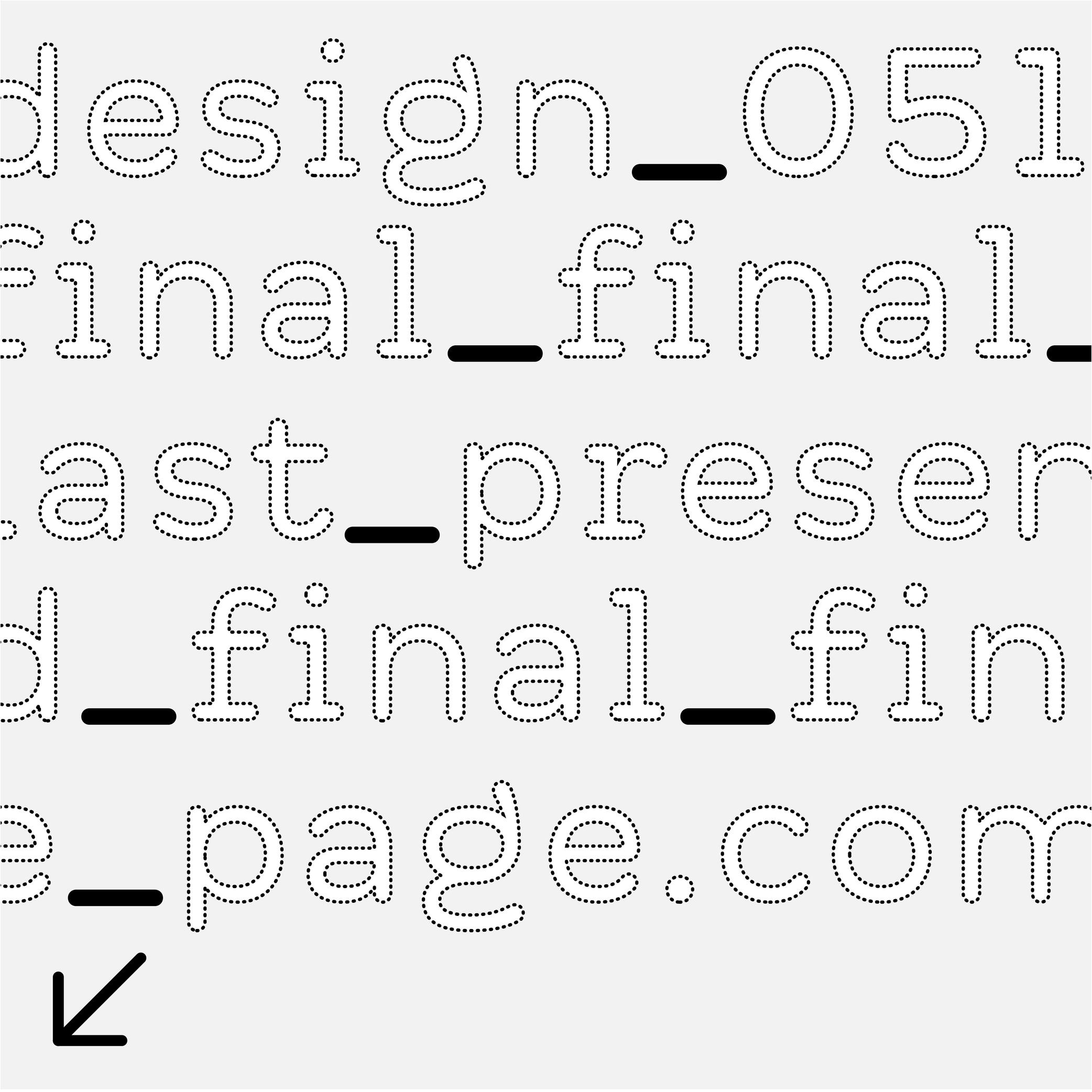
功能
下划线如今主要用作分隔单词的标记,只要空格无效(URL 或电子邮件地址、文件名等)。
历史
在欧洲图书出版惯例中,在手稿中给单词或句子加下划线是为了通知字体排印师或印刷工将其设置为斜体(或罗马体)。
该符号一直保留在打字机和现代键盘上,用于不同语言的各种用途,是一个单独的符号,而不是与其他字形组合在一起的标记。
设计
下划线是一个类似破折号的字形,位于基线下方,长度(通常)与半角破折号相同。
字体排印的规则
下划线两侧没有空格。 不要混淆 我们通常称这个字形为 “下划线”。但是,它的合适的名称应该是 “底线”(在 Unicode 命名中使用正确的代码),因为下划线 (U+0332) 是非洲和美洲土著语言中使用的组合符号。
UNICODE 编码
LOW LINE: U+005F